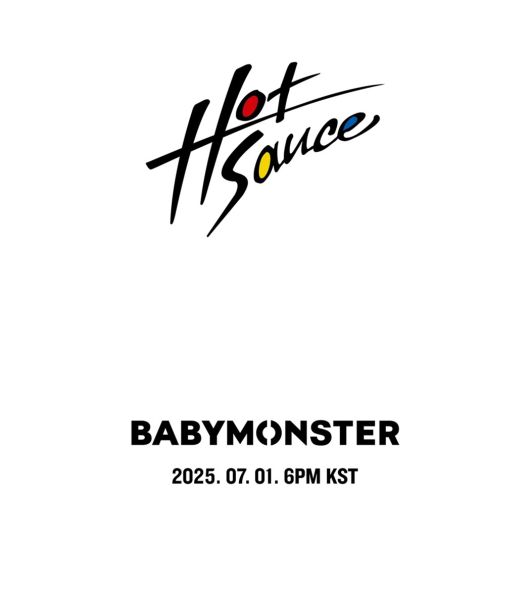
(서울=뉴스1) 고승아 기자 = 그룹 베이비몬스터가 신곡 '핫 소스'(HOT SAUCE) 일부 음원이 들어간 티저를 처음 공개했다.
소속사 YG엔터테인먼트는 24일 공식 블로그를 통해 베이비몬스터의 신곡 '핫 소스' 로고 무빙 티저를 게재했다.
특히 '핫 소스' 폰트가 눈길을 끈다. YG의 수장이자 베이비몬스터를 탄생시킨 양현석 총괄이 1992년 서태지와 아이들로 데뷔한 당시 1집 앨범에 적힌 폰트를 오마주했다.
1980년대의 올드스쿨 힙합 사운드를 예고한 베이비몬스터의 신곡 콘셉트와 맞물려 1992년 발매된 서태지와 아이들의 1집 앨범 폰트를 재소환하여 옛 감성을 자극한 것이다.